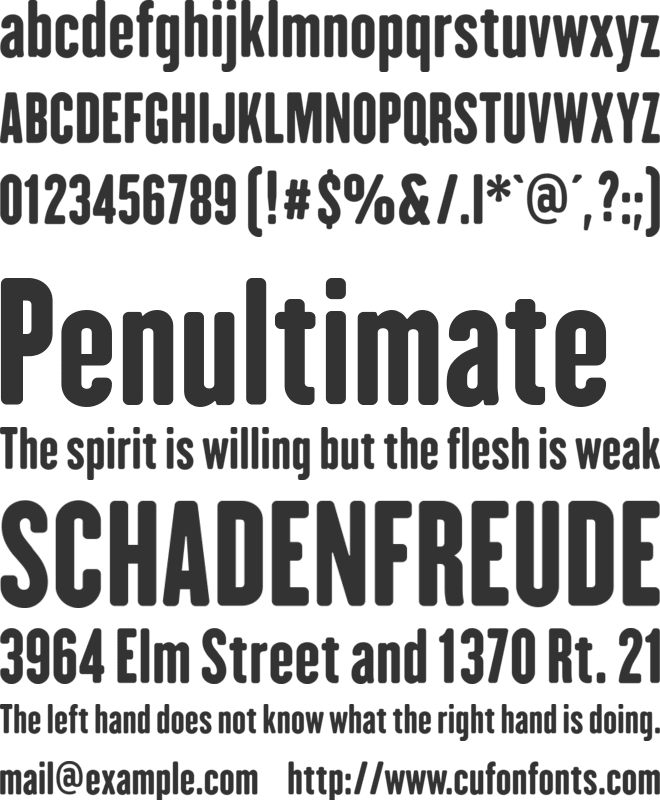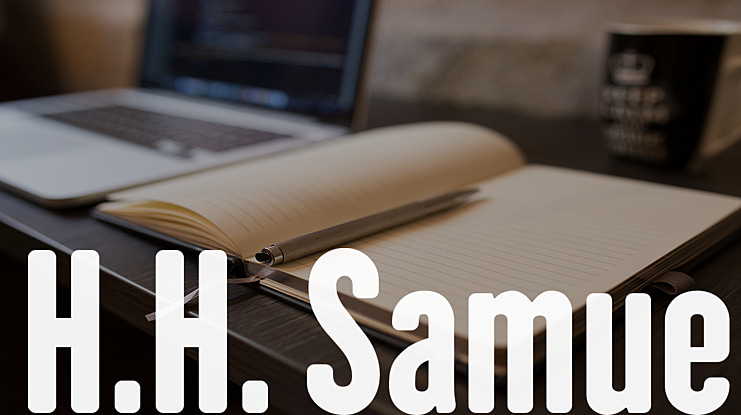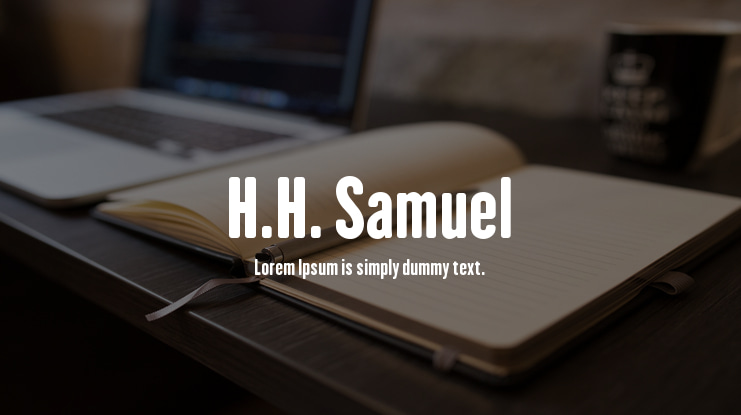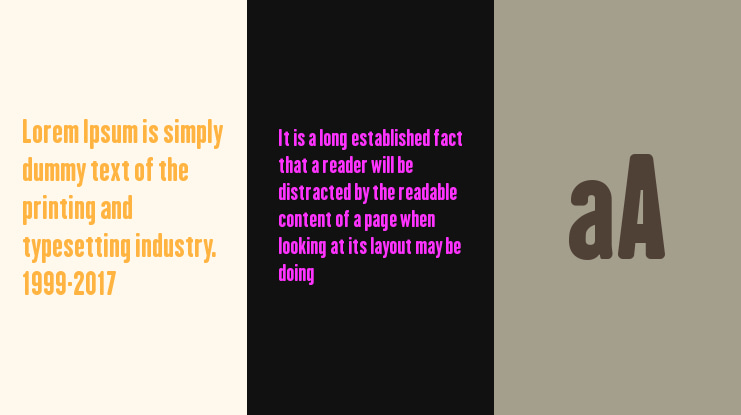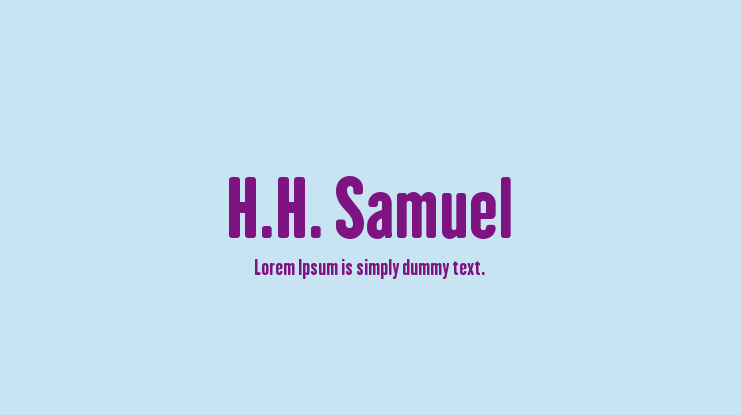
H.H. Samuel Font
H.H. Samuel es mi nuevo diseño tipográfico, una fuente geométrica, extra condensada, sin serifa, con acabado redondeado en los vértices que le da más luz a las contraformas de la fuente. Está inspirada en las fuentes grotescas y humanistas condensadas de principios y mediados del siglo XX. y conserva un estilo retro, la fuente la he diseñado con una proporcion de 1:2,28.